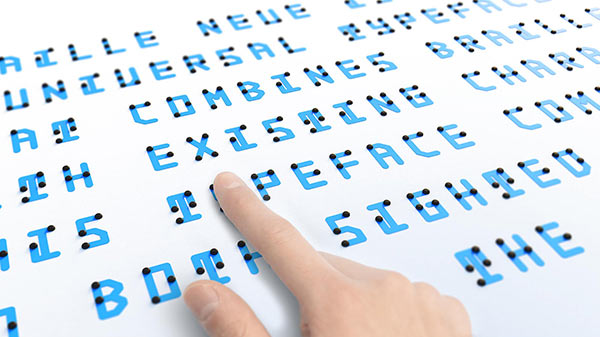
പുതിയ ലാറ്റിന്, ജാപ്പനീസ് ഫോണ്ടുകള് കൂട്ടിച്ചേര്ക്കുന്നു ബ്രെയ്ലി
അന്ധരായ ആളുകളെ എഴുതുവാനും വായിക്കുവാനും പ്രാപ്തരാക്കിയ ലിപി സബ്രാദായമാണ് ബ്രെയ്ലി ലിപി അഥവാ ബ്രെയിലി സമ്പ്രദായം. ഇപ്പോള് മറ്റൊരു അത്ഭുതവുമായി എത്തിയിരിക്കുകയാണ് ബ്രെയ്ലി.
അതായത് ജാപ്പനീസ് ഡിസൈനര് കോസ്യൂകെ തകഹാര്ഷി ഒരു പുതിയ ടൈപ്പ് ഫെയ്സ് സൃഷ്ടിച്ചു. 24 വയസ്സുളള ഇദ്ദേഹം സൃഷ്ടിച്ച ബ്രെയ്ലി ന്യൂ ടൈപ്പ്ഫേസസ് (Braille Neue typefaces) ഇംഗ്ലീഷ് ജാപ്പനീസ് എന്നീ പ്രതീകങ്ങള് തുല്യമായി പൊതിഞ്ഞിരിക്കുന്നു.
ജനപ്രിയ ഹെല്വെറ്റിക്ക ന്യൂ ഫോണ്ടില് നിന്ന് ഉത്ഭവിക്കപ്പെട്ട ബ്രെയ്ലി ന്യൂ, രണ്ട് രീതികളിലാണ് എത്തിയിരിക്കുന്നത്. ഒന്ന് ബ്രെയ്ലി ന്യൂ സ്റ്റാന്ഡേര്ഡ് (Braille Neue Standard) ഇംഗ്ലീഷ് മറ്റൊന്ന് ബ്രെയ്ലി ന്യൂ ഔട്ട്ലൈന് (Braille Neue Outline) ഇംഗ്ലീഷും ജാപ്പനീസും. മിക്ക കാഴ്ചക്കാര്ക്കും ബ്രെയ്ലി വായിക്കാന് കഴിയാത്തതിനാല് ഒരോ അക്ഷരവും, കാഴ്ചക്കാര്ക്കും അന്ധര്ക്കും തമ്മില് എളുപ്പത്തില് വിവരങ്ങള് കൈമാറാന് സാധിക്കുന്നു.
ബ്രെയ്ലി ന്യൂ ഔട്ട്ലൈന് എല്ലാവര്ക്കും കൂടുതല് ആക്സസ് ചെയ്യാനായി പൊതു ഇടങ്ങളില് ഓവര്ലെയ്ഡ് ചെയ്തതായിരിക്കും. കൂടാതെ പൊതുയിടങ്ങളില് വലിയ ഫോര്മാറ്റും ആയിരിക്കും രൂപകല്പന ചെയ്യുന്നത്. കൂടാതെ ഇത് ഉടന് തന്നെ പൊതു ഉപയോഗത്തിന് എത്തുകയും ചെയ്യും എന്ന് ബ്രെയ്ലി ന്യൂ പറഞ്ഞു.
2020ലെ ടോക്കിയോ ഒളിംബിക്സിലും പാരലിംപിക്സിലും ഇത് ഒരു സ്റ്റാന്ഡേര്ഡ് ആയിരിക്കുമെന്ന് തകാഹര്ഷി പ്രതീക്ഷിക്കുന്നു.